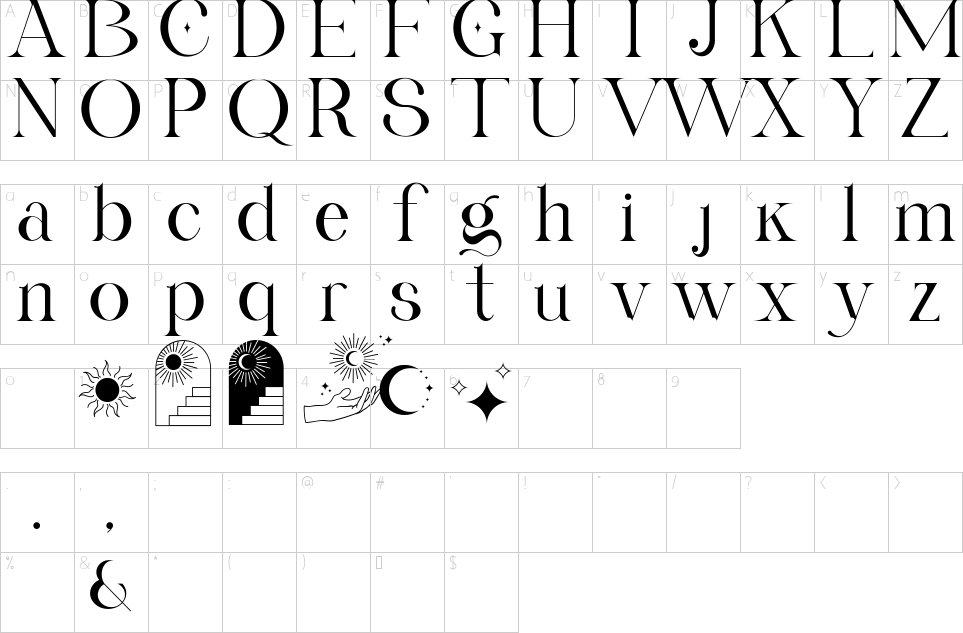
A Gyahegi Font é uma oferta gratuita disponível no site 1001 Free Fonts para usuários dos sistemas Windows e Mac. Desenvolvida por Putu Dody Permana, esta elegante e sofisticada fonte está repleta de detalhes que irão enriquecer qualquer projeto gráfico. Com seu design meticuloso e criativo, a Gyahegi pode adicionar um toque único à sua identidade visual ou adicionar profundidade ao texto em suas páginas web e projetos impressos. Com apenas 343 downloads até o momento, esta font é uma oportunidade de experimentar algo novo sem comprometer seu orçamento. Com um design moderno, a Gyahegi oferece opções para personalizar texturas e estilos, criando visuais que vão muito além das fontes comuns. Embarque nesta experiência gratuita de alta qualidade e descubra por si mesmo as possibilidades da Gyahegi Font.
Mapa de caracteres da fonte Gyahegi Font - 1001 Free Fonts